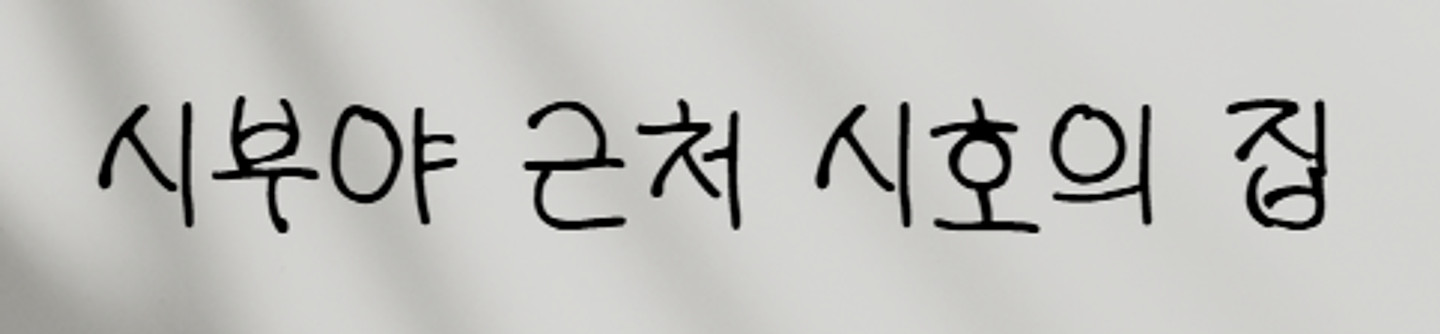
야노시호님 유튜브에 등장한 폰트인데 무슨 폰트인지 아시는분 계실까요 ㅠㅠ 도쿄 가기 전 필수 시청🗼시호 핫플 전부 공개 (ft.쇼핑, 라멘 맛집, 카페) https://youtu.be/NM18C7JZHOE?si=XVQHZv74bUtxSk4B 0:31 에 등장한 폰트인데 무슨 폰트인지 아시는분 계실까요 ㅠㅠ